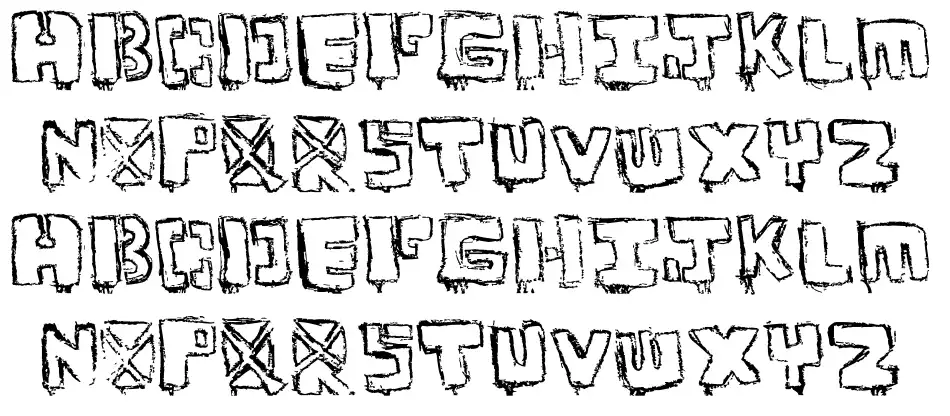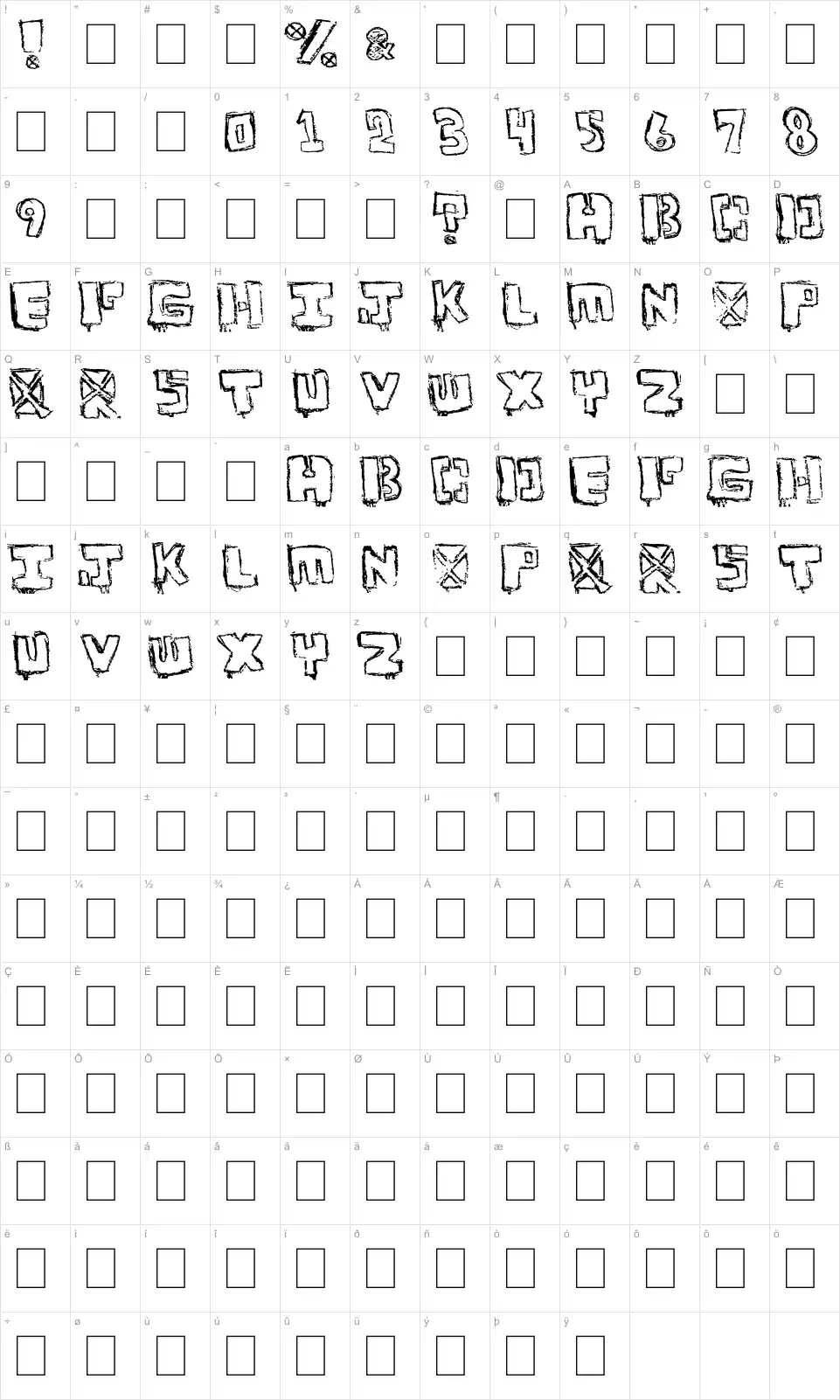
A fonte Your Font, criada pelo designer Nour, oferece um estilo chamativo e arrojado ideal para criar designs originais e atrativos. Esta fonte, disponível em formato TTF, faz parte da categoria Fancy, sendo particularmente adequada para trabalhos que desejam criar um efeito de destaque e destempero. Se você está procurando por uma fonte única e interessante, o Your Font de Nour é uma excelente escolha. Possui uma licença aberta, facilitando o uso em projetos pessoais e comerciais. Além disso, é fácil de usar e pode ser baixada em formato TTF, permitindo que você personalize a fonte conforme necessário. O seu tamanho compacto (92 KB) facilita o armazenamento e permite um uso rápido em projetos. Com 2001 downloads até o momento, acredita-se que já haja muitos usuários que já experimentaram a sua versão destemperada, apreciando a maneira como ela destaca o texto. A sua categoria de “Destroy” sugere que a fonte pode criar efeitos desafiadores e criativos, tornando-se um recurso valioso para designers em busca de algo mais que agradável. Se você estiver considerando incorporar uma fonte como essa ao seu portfolio ou projeto, é uma escolha que merece uma oportunidade.